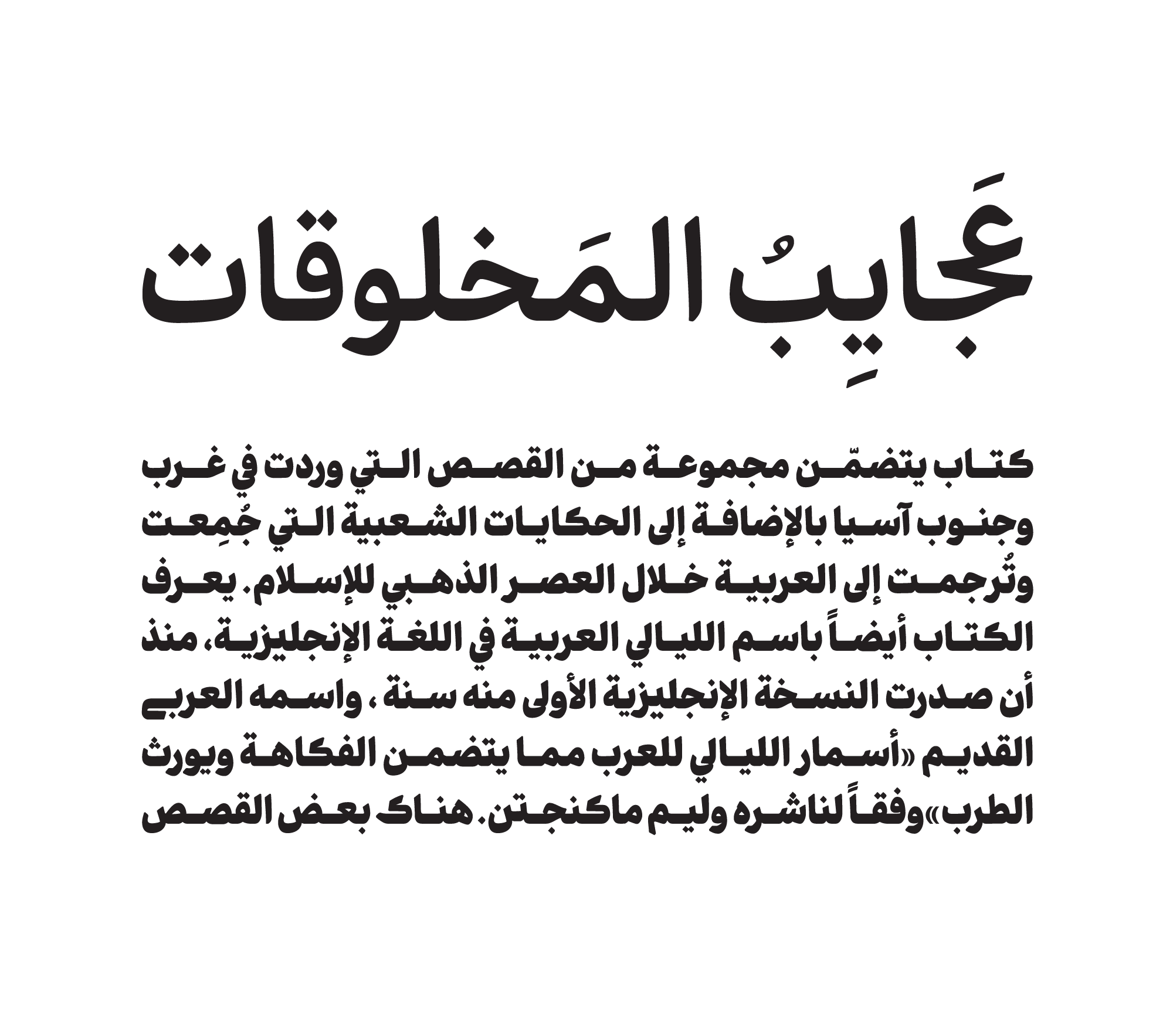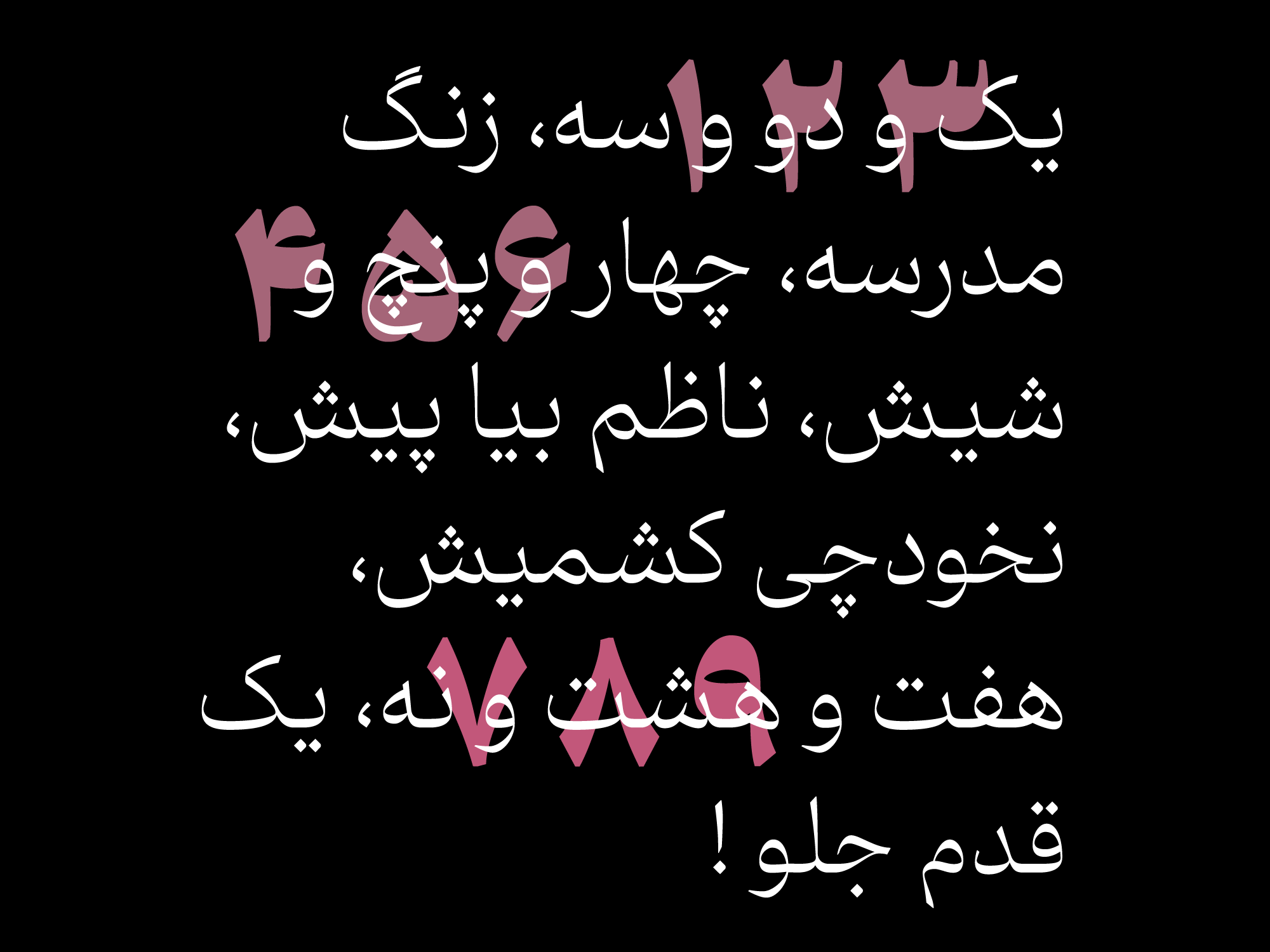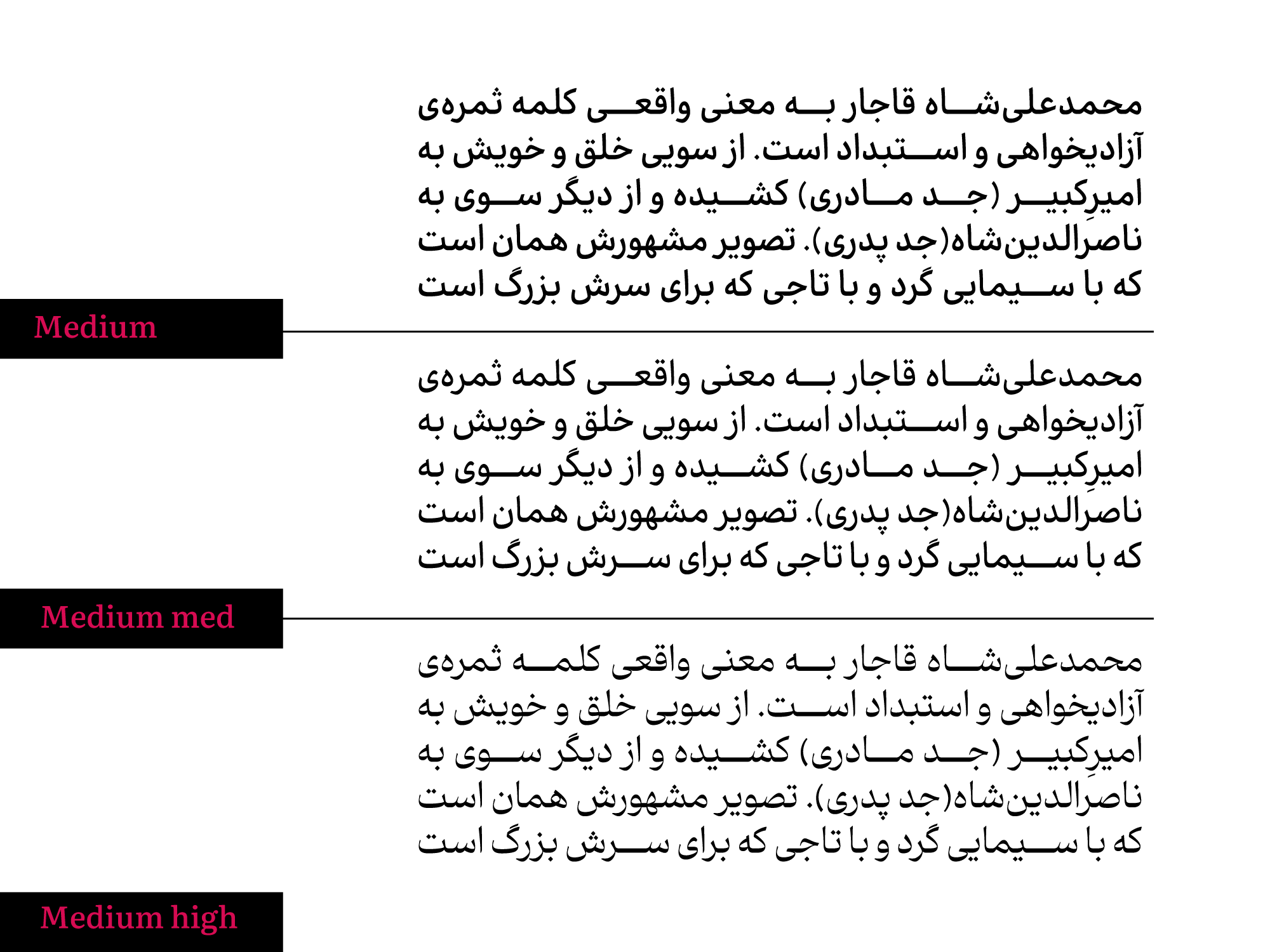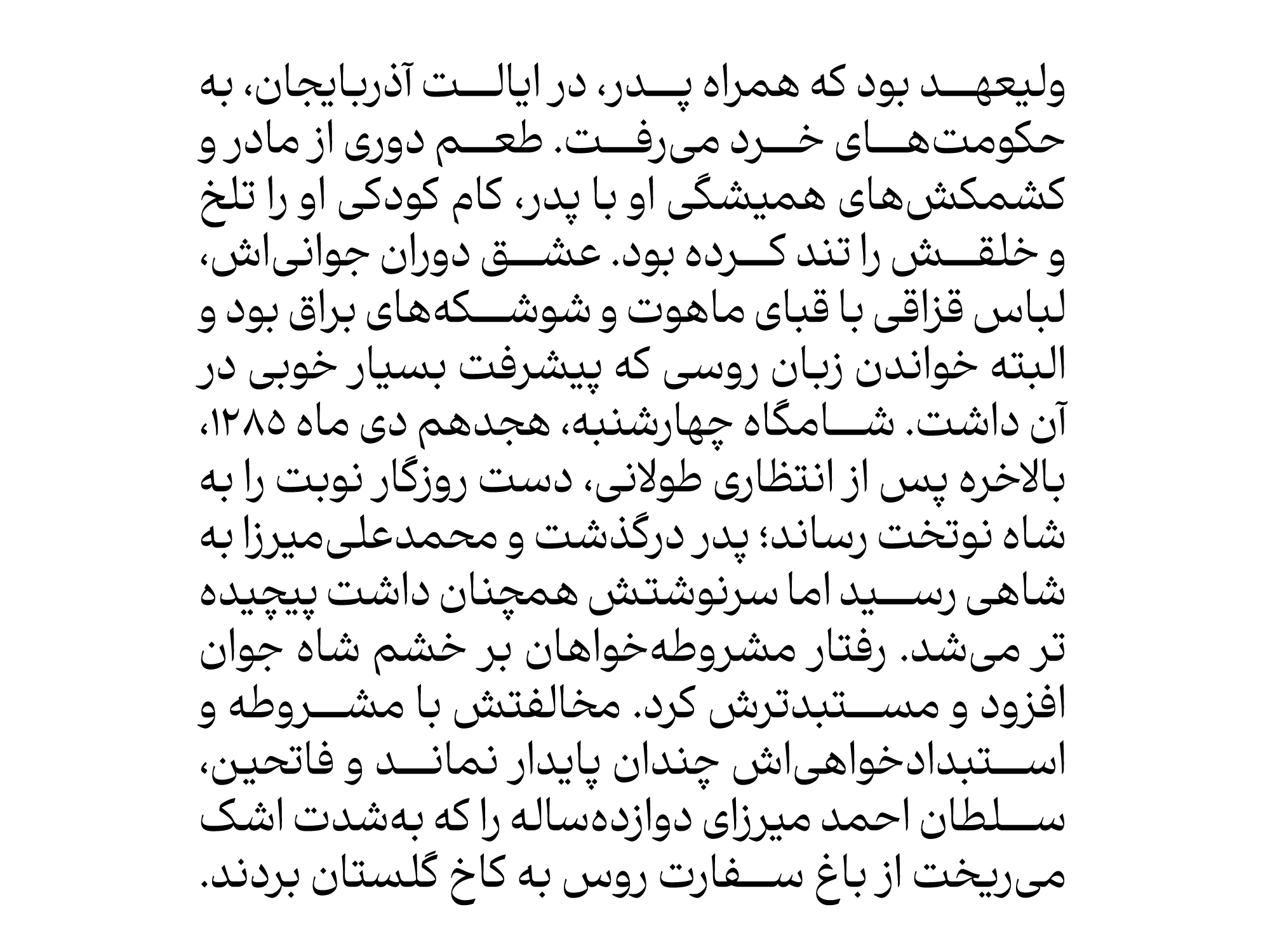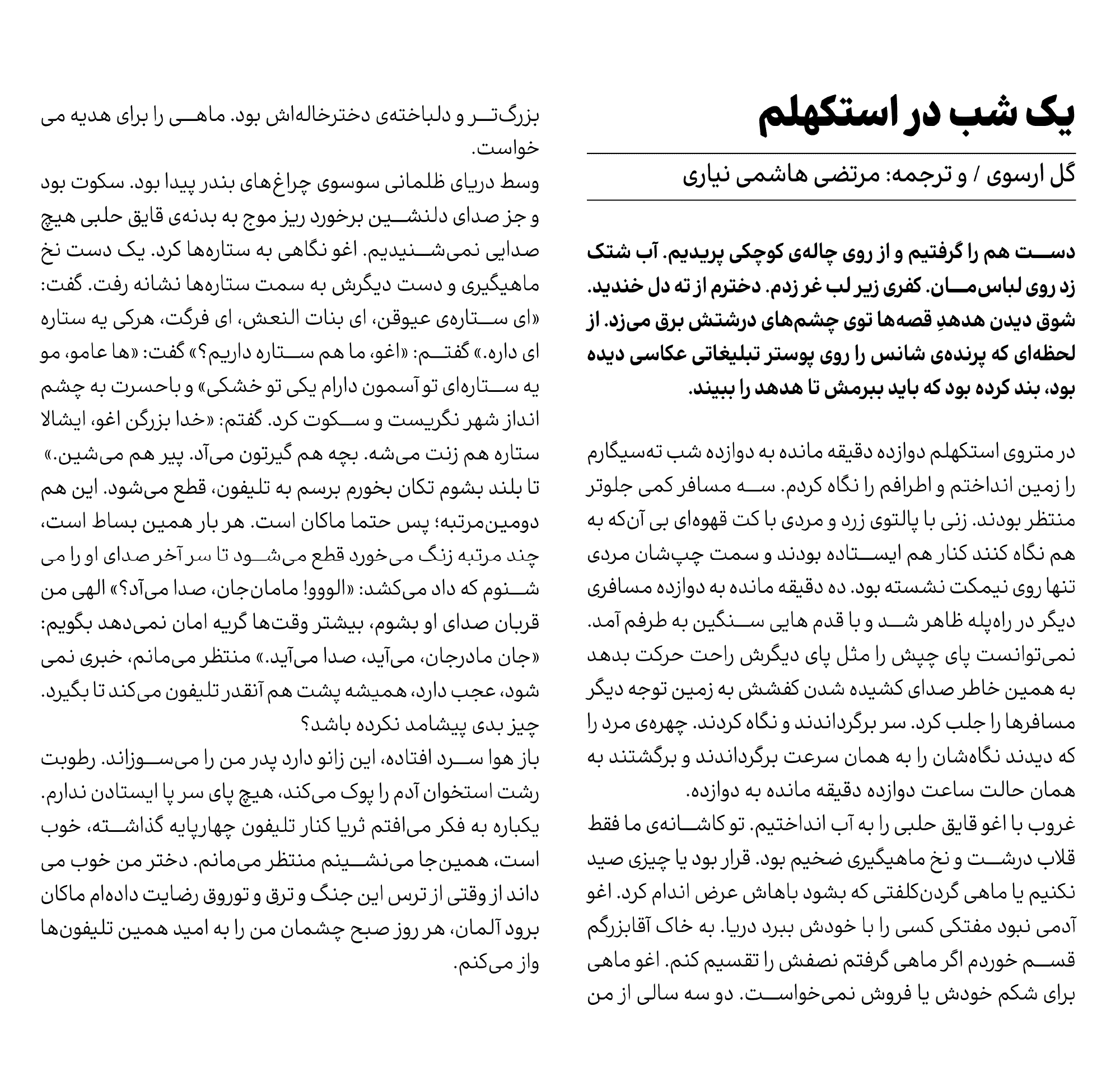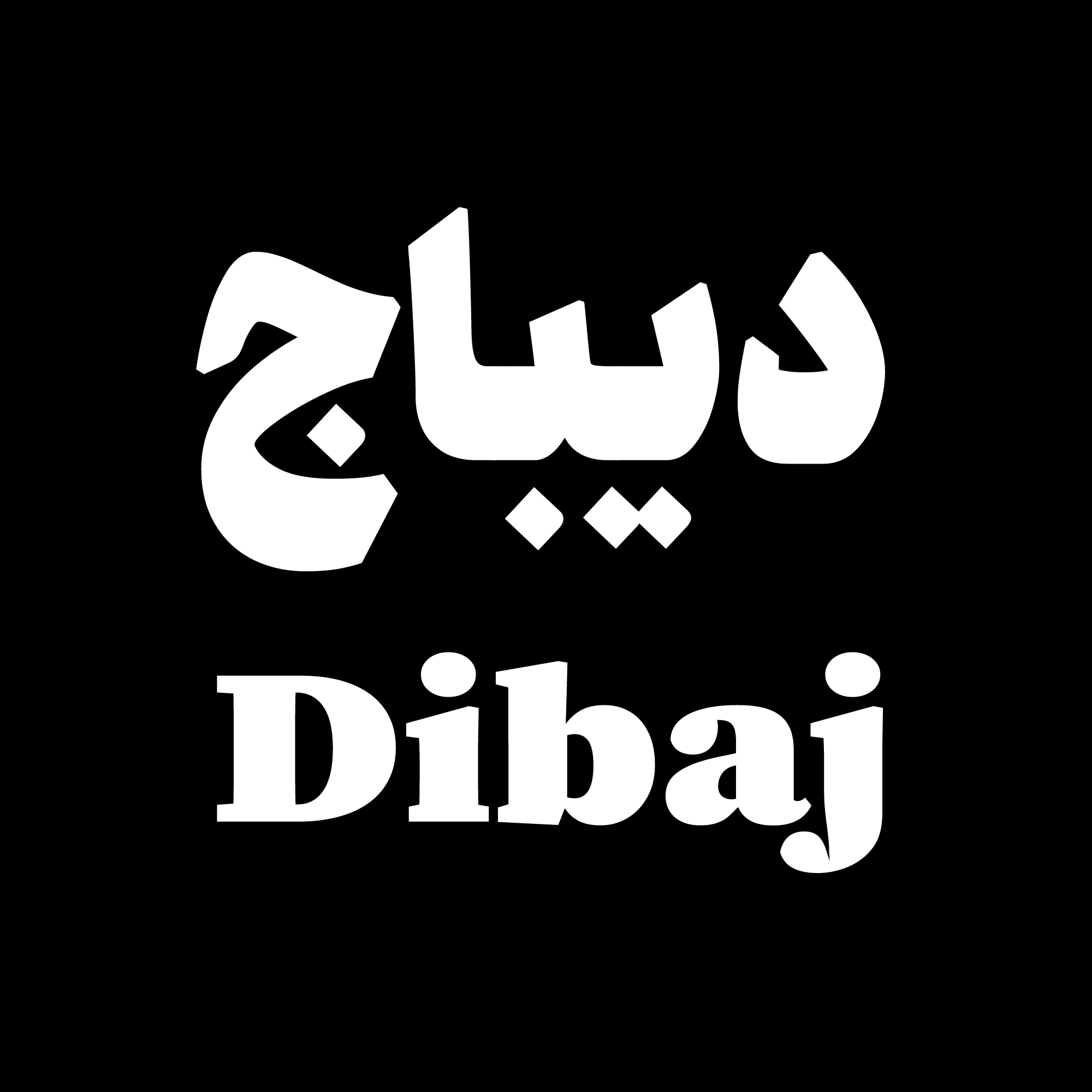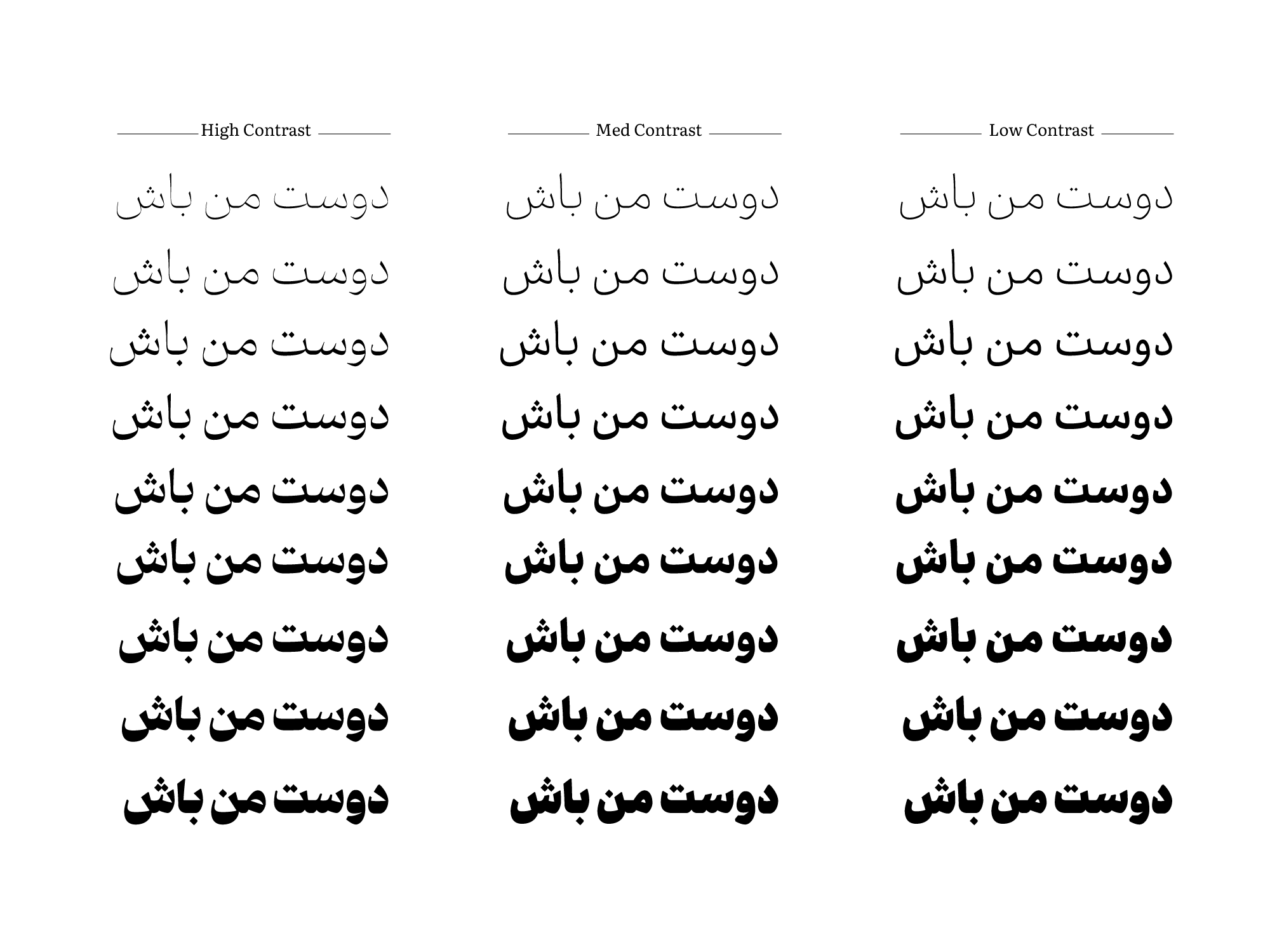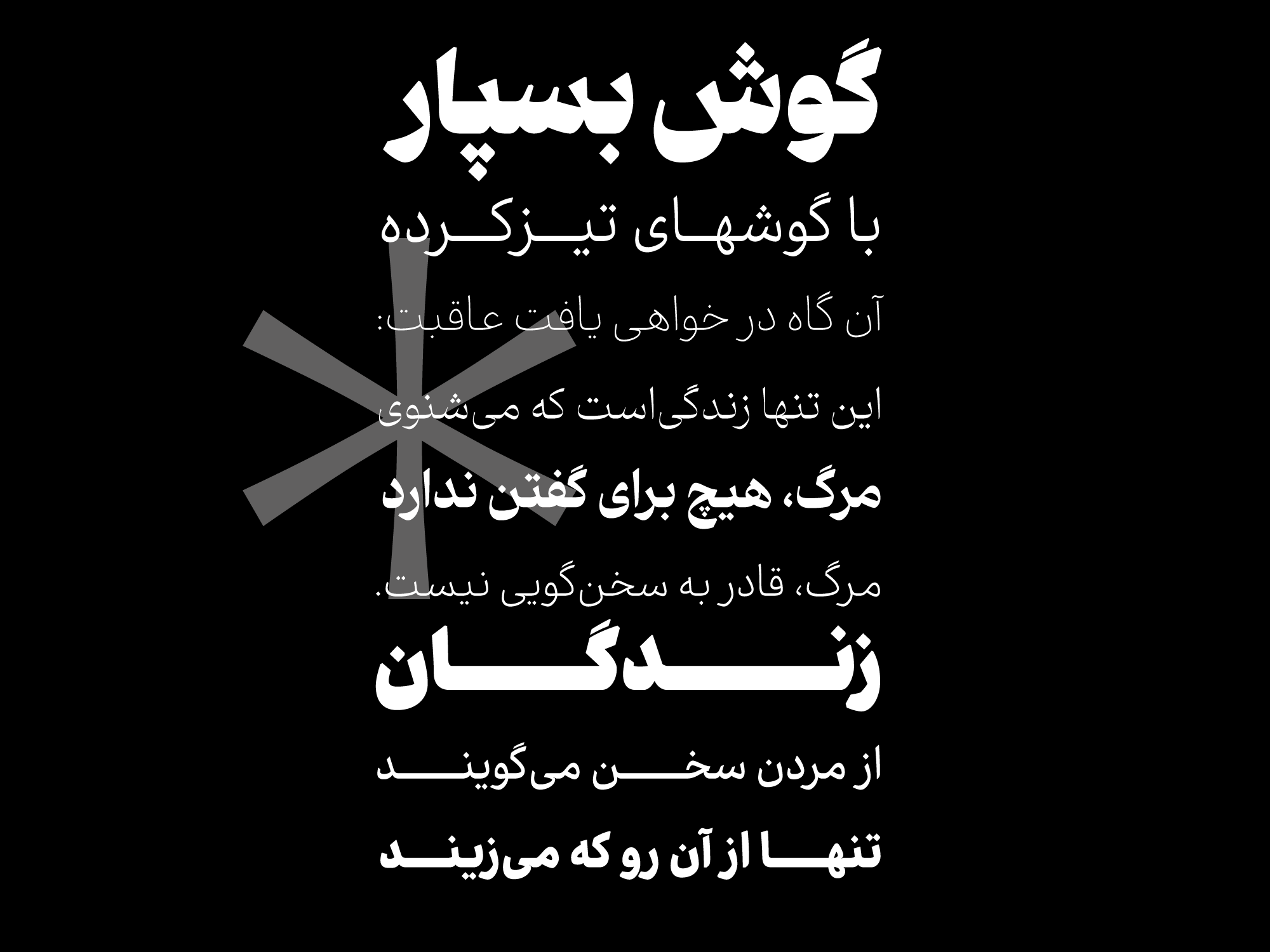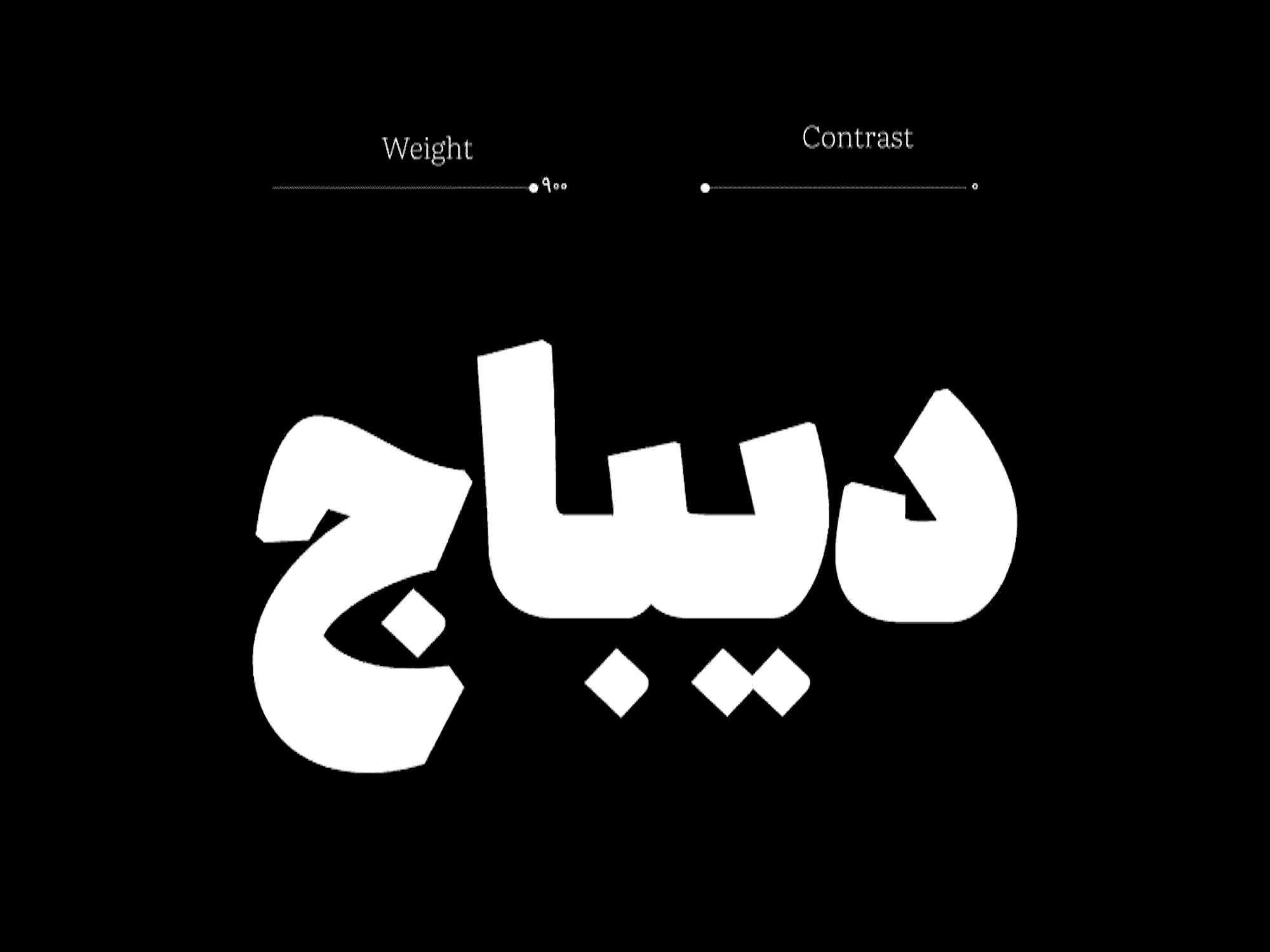
فونت دیباج از زبان فارسی، عربی و انگلیسی پشتیبانی میکند.
بسته حرفه ای فونت دیباج دارای 9وزن (Extra light, Light, Regular, Medium, Semi Bold, Bold, Extra bold, Black, Extra Black) و سه حالت ضخامتیLow contrast, Medium contrast, High contrast و نسخهی وریبل است.
در واقع کاربر در نسخه وریبل این بسته، میتواند علاوه بر تغییر وزنها، سبک نوشتاری خود را نیز تغییر دهد. بسته حرفهای دیباج، شخصیتها و لحنهای مختلفی از حروف را در اختیار کاربر قرار میدهد تا در طیف موضوعی گسترهتری بتواند از این فونت استفاده نماید.
فونت دیباج علاوه بر زبان فارسی، گلیف های عربی، کوردی، لری، مازندرانی، اردو و افغانی را پشتیبانی میکند
فونت کتاب و مجله؛ صفحات کاغذی تا الکترونیکی